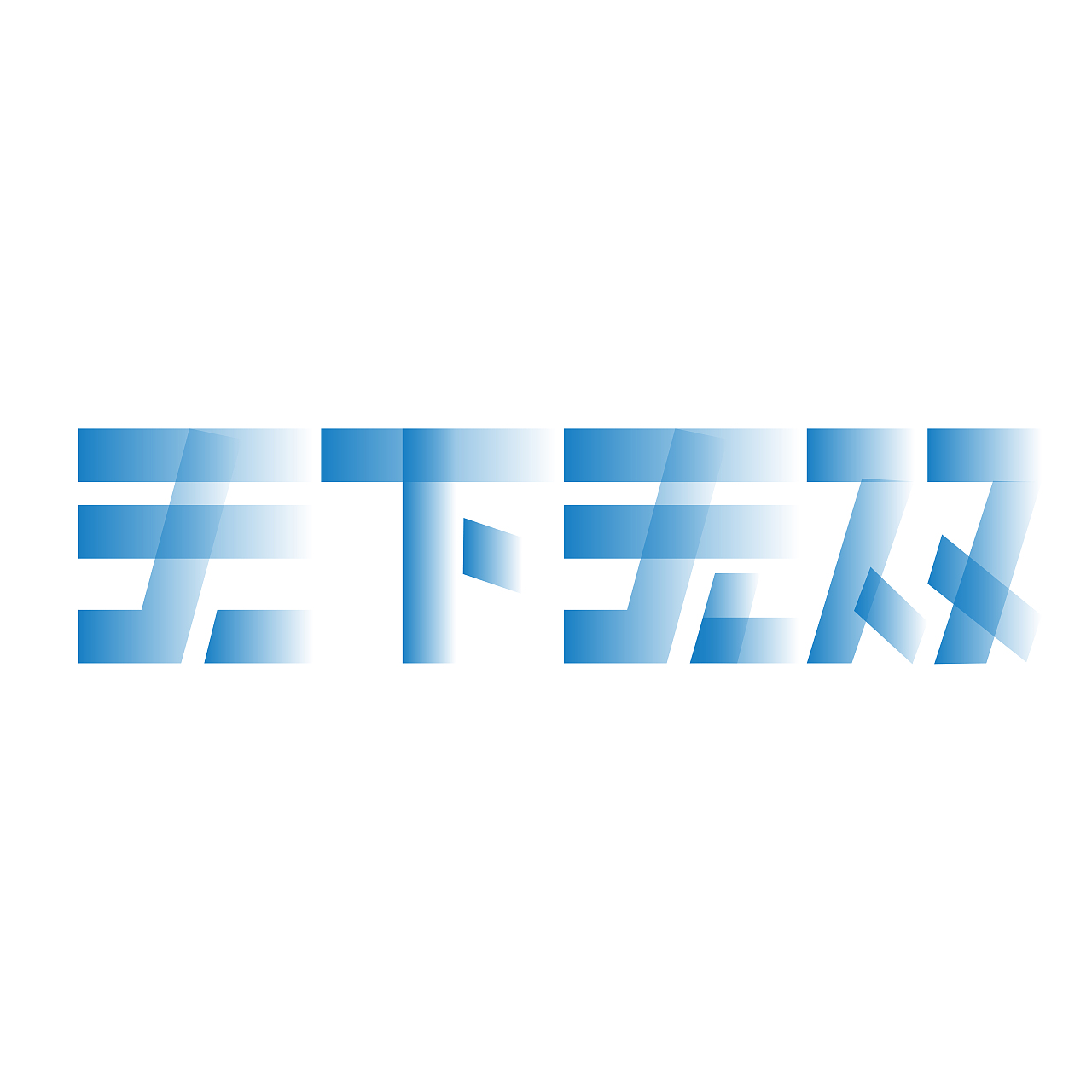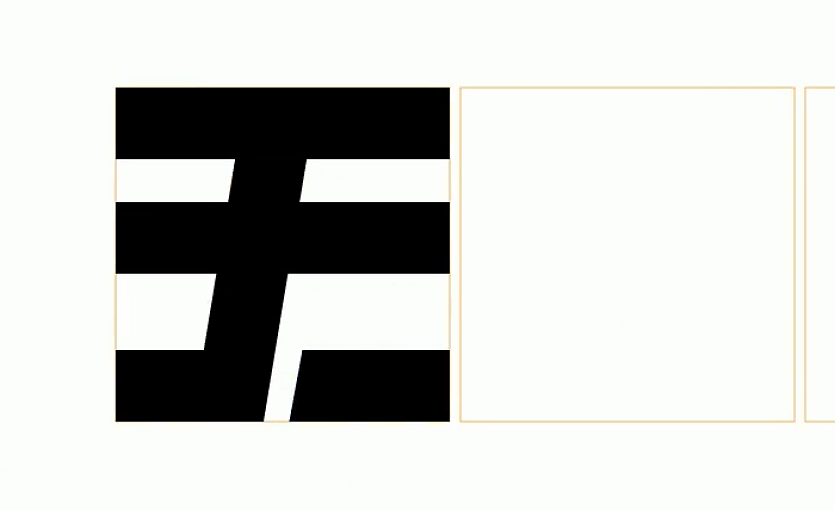
用ai的矩形工具 绘制出字体字形、
设计出自己想要的感觉 这次设计字体的基本形状只用了矩形工具
再利用路径查找器对字形进行变化
对logo的颜色做一个变化
最后得出自己想要的作品
最后的效果图
用了渐变的颜色效果
这是没有把整体做连集的效果
有的人喜欢这种风格可以这样尝试
内部字形的交接看的很清楚
这是把所有选中
在路径查找器做一个连集的效果
也做了渐变
首先建四个矩形框
方便进行字体变化
用矩形工具按笔画笔顺做出变化
第一个字是“天”
根据自己要的感觉去设计
“天”字的基本型是这样
“天下无双”几个字的基本字形设计好后是这样
可以自己的想法去做改变
最后简单的加个渐变颜色
也可以加一些装饰框等等
字形上也可以进一步深入变化和设计